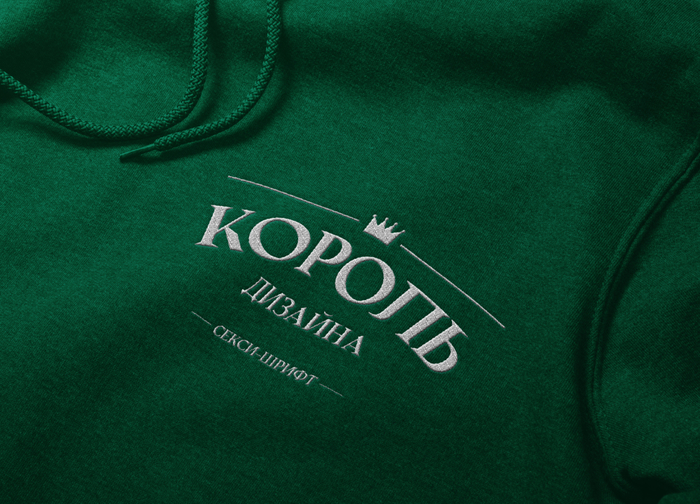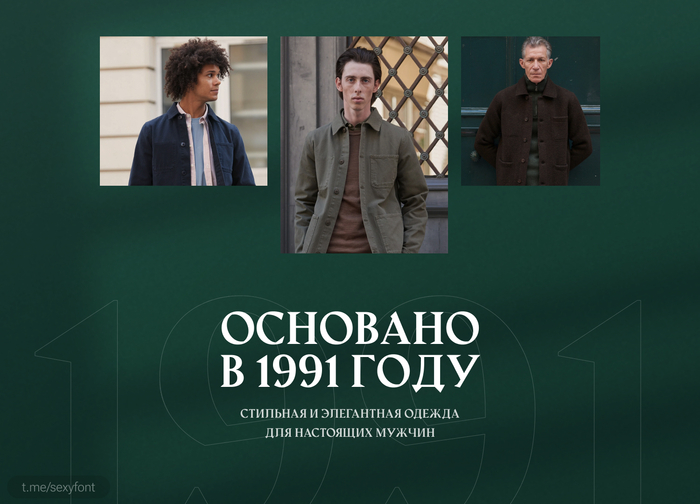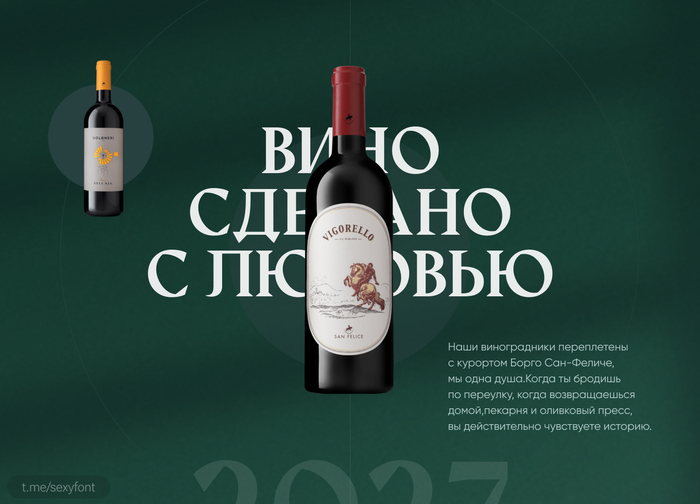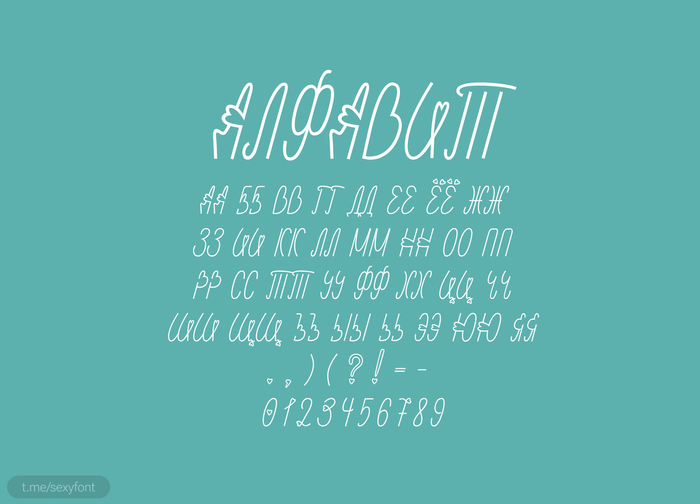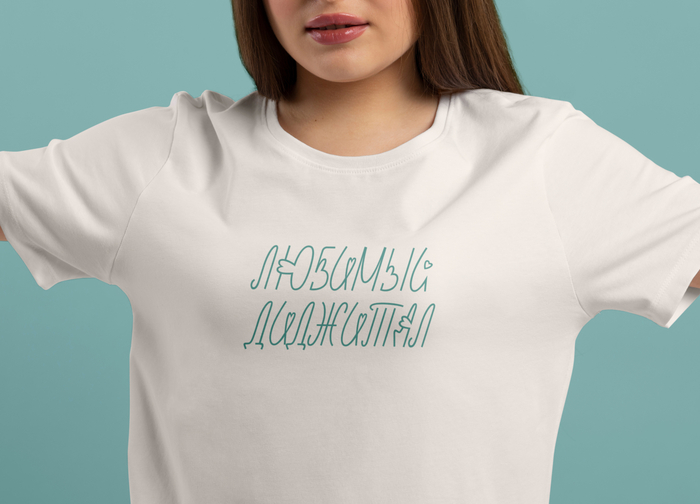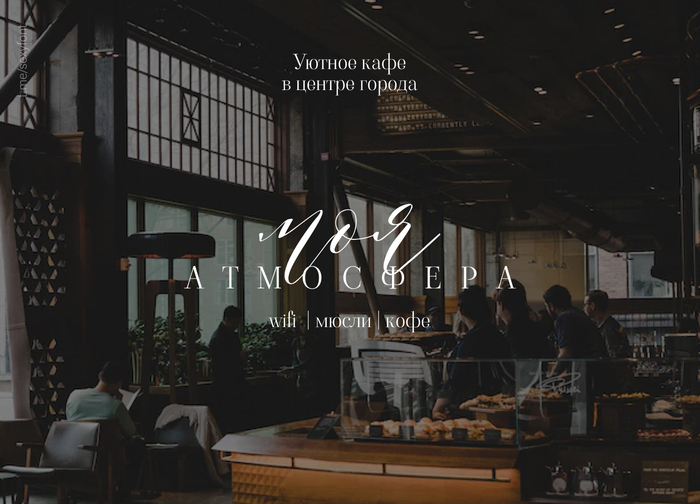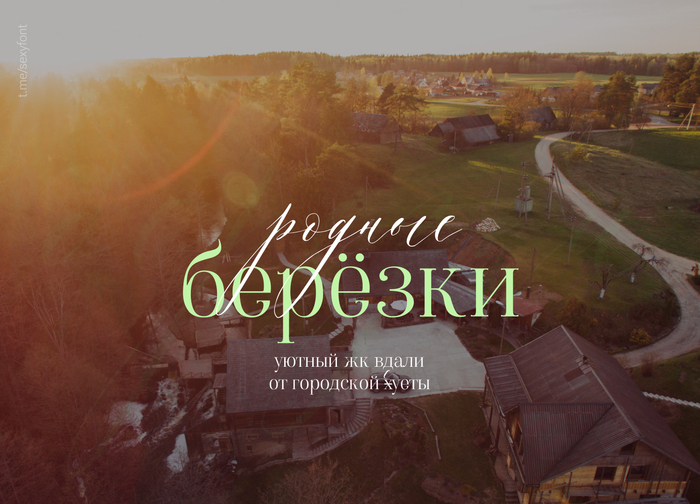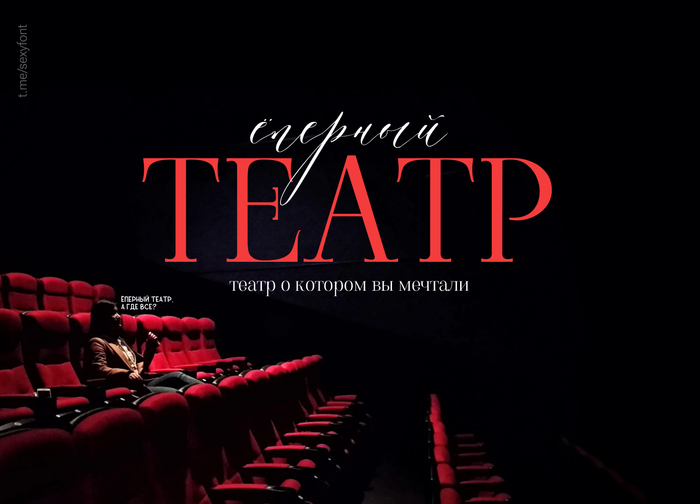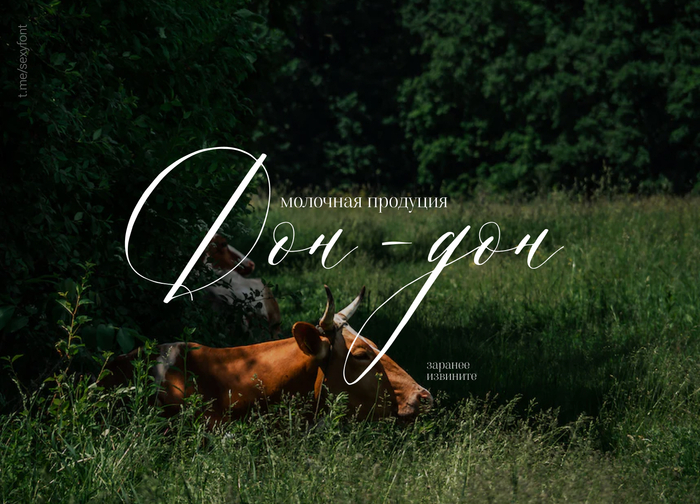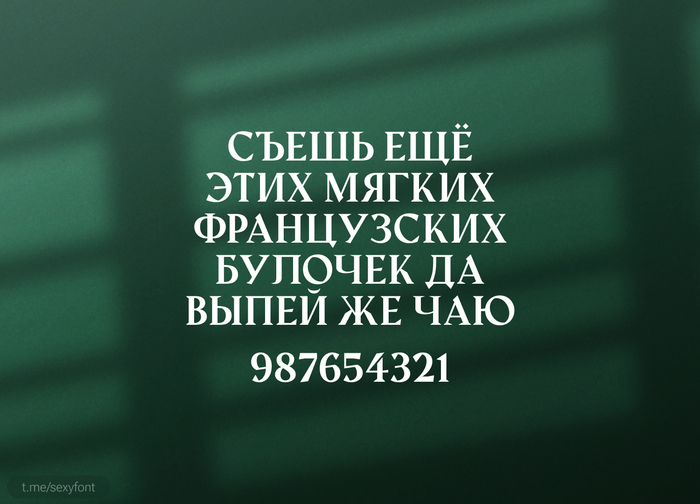
Caravan + viaoda libre
Сегодня сочетание слабо читаемого, но красивого курсива Caravan. А так же симпатичная антиква Viaoda libre. Первый бесплатен для личного использования. Второй полностью.
Шрифт Amagro. Кириллица
Новая презентация. Шрифт Amagro. Увесистый, контрастный с небольшими засечками.
Автор: Fabio Servolo
Шрифт DD_Font. Кириллица
Минутка милашества. Романтичный, сердешный шрифт для ваших проектов.
Автор: Rita Schmurz
Шрифт Gorod. Кириллица
Gorod. Мощный, уверенный и увесистый шрифт. Подойдет для крупных заголовков.
Автор: Ilya Zakharov
Шрифт Yulong. Бесплатная кириллица
Yulong. Сжатый геометрический шрифт, состоящий из двух стилей. Благодаря своему индустриальному виду шрифт подходит для логотипов, крупных заголовков, плакатов, вывесок, принтов, шрифтовых композиций, а также для макетов, связанных с технологиями и киберспортом.
Автор: GGBotNet
Шрифт Blackcraft. Кириллица
Blackcraft. Дерзкий, как пуля резкий, декоративный шрифт для крупных заголовков. Автор: GGBot. Бесплатно для личного и коммерческого использования.
Бесплатный шрифт lozung
Lozung. Мощный, динамичный шрифт. Отлично впишется под спортивные тематики или плакаты. Кто-то, чтобы начать бегать покупает кроссовки. Дизайнеру достаточно установить шрифт 😁 Нам этом данное мероприятие можно и закончить.
Black holey. Или Черная дыра. Нечитаемость уровень 10000
От автора: Я разрабатывала её для выставки (студенческий проект в HSE) - сделала презентацию, где показываю как на основе шрифта строится фирмач. Он очень акцидентный, поэтому только для заголовков - только прописные буквы))
+ есть цифры, и самые популярные знаки препинания.